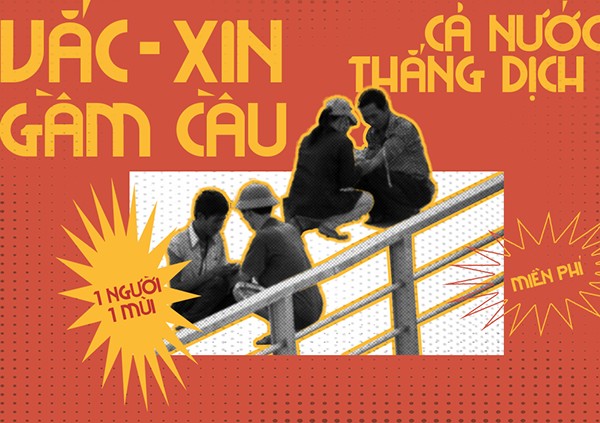
Font Tiếng Việt Doc Lap – Đặng Anh Khoa – Font Chữ Việt Hóa Độc Đáo Cho Học Đường
Trong thế giới thiết kế đồ họa Việt Nam, việc tìm kiếm một bộ font mang đậm bản sắc dân tộc nhưng vẫn giữ được nét hiện đại là điều không hề dễ dàng. Font Tiếng Việt Doc Lap – Đặng Anh Khoa là một tác phẩm typography đặc biệt, được tạo ra nhằm tôn vinh giá trị lịch sử và tinh thần tự do. Đối với các bạn học sinh và thầy cô giáo, việc sử dụng Font Chữ đẹp không chỉ làm nổi bật nội dung trình bày mà còn truyền tải được thông điệp ý nghĩa qua từng nét chữ Việt hóa chỉn chu.
Ưu điểm nổi bật của Font Tiếng Việt Doc Lap – Đặng Anh Khoa
Bộ font này được cộng đồng thiết kế đánh giá cao nhờ sự kết hợp hài hòa giữa cấu trúc chữ cổ điển và phong cách tối giản đương đại. Tác giả Đặng Anh Khoa đã tỉ mỉ tinh chỉnh từng dấu câu để đảm bảo hiển thị hoàn hảo trên các phần mềm phổ biến.
Thiết kế tối ưu cho tiếng Việt
Điểm mạnh nhất của Font Tiếng Việt Doc Lap – Đặng Anh Khoa chính là khả năng hiển thị các ký tự đặc biệt như ă, â, đ, hay các dấu thanh một cách tự nhiên, không bị lỗi font hay đè dấu. Điều này cực kỳ quan trọng khi thực hiện các bài thuyết trình hay thiết kế poster trường học.
Ứng dụng đa dạng trong giáo dục
Nhờ vẻ ngoài nghiêm túc nhưng vẫn mềm mại, font chữ này rất phù hợp để làm tiêu đề bài giảng, thiệp mời sự kiện hoặc các ấn phẩm tuyên truyền tại các cơ sở giáo dục. Nó mang đến cảm giác gần gũi và đầy tự hào dân tộc.
Cách sử dụng Font Tiếng Việt Doc Lap – Đặng Anh Khoa hiệu quả
Để phát huy tối đa vẻ đẹp của bộ font này, bạn nên kết hợp với những tông màu trầm ấm như đỏ đô, vàng đất hoặc xanh lá đậm. Việc phân cấp chữ tiêu đề và nội dung bằng cách thay đổi kích cỡ sẽ tạo nên một bố cục hài hòa và chuyên nghiệp cho tài liệu của bạn.